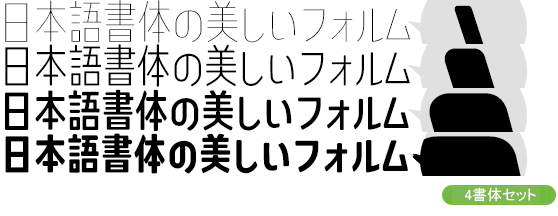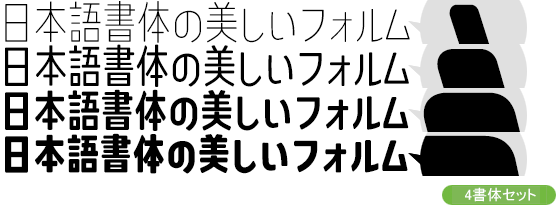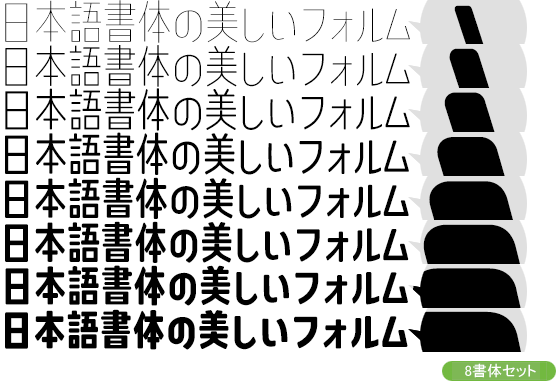
コトノモ コンデンス Kw-N Light
Kotonomo-Condensed-Light-Kw-N
スタイリッシュでやさしい印象のある、縦長・超極細の丸ゴシック体です。
通常のフォントより上下に飛び出しているデザインのため、ご利用のアプリによっては見切れる場合があることを、ご了承ください。
収録文字:8007文字
ひらがな・カタカナ・アルファベット・数字・一部の記号漢字(JIS第一水準・JIS第二水準・IBM拡張漢字、その他の独自選定漢字)jis2004字形
※ 「㌢」「㈱」「㊤」などの組文字・囲み文字、「┨」などの罫線、「Ж」などのキリル文字は含まれていません